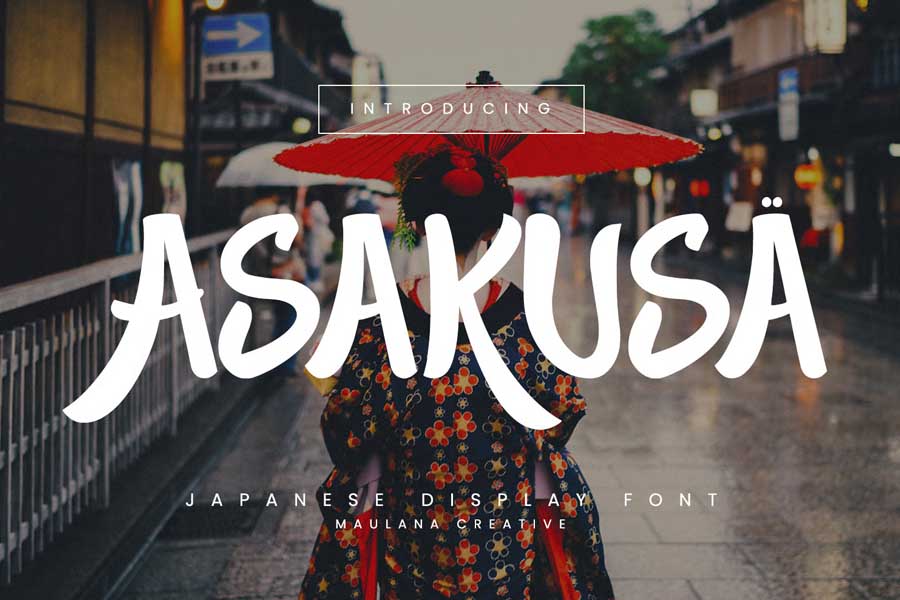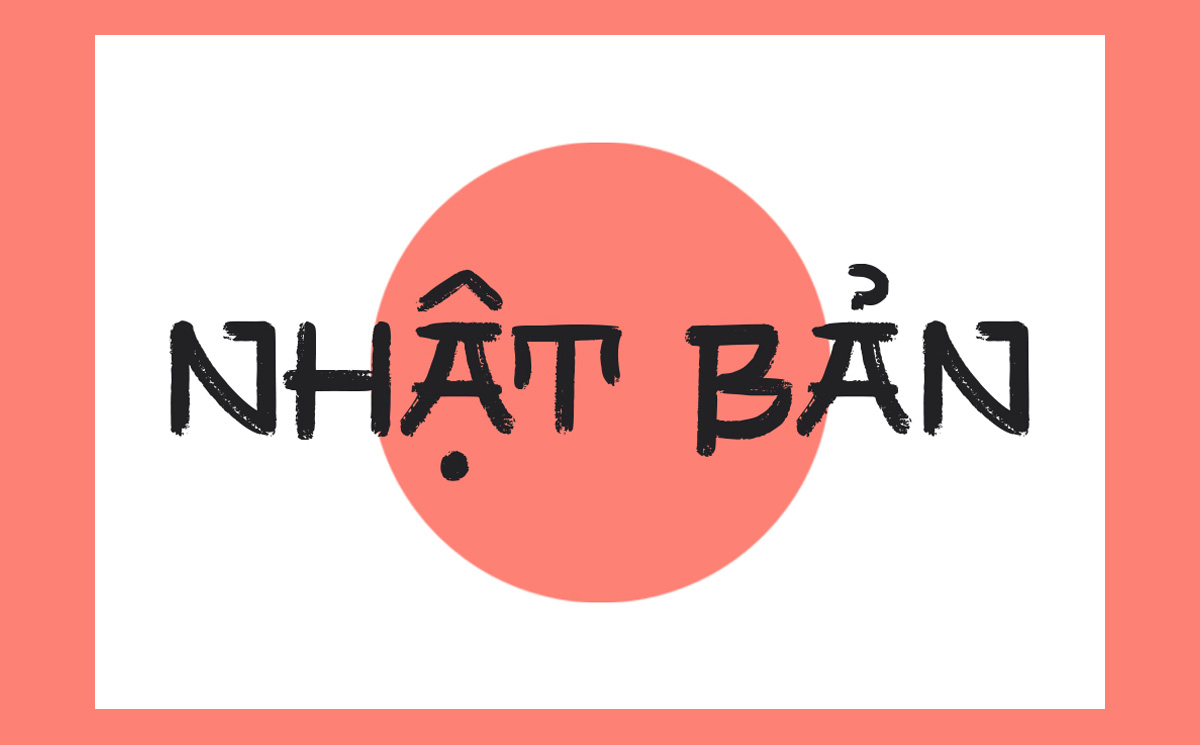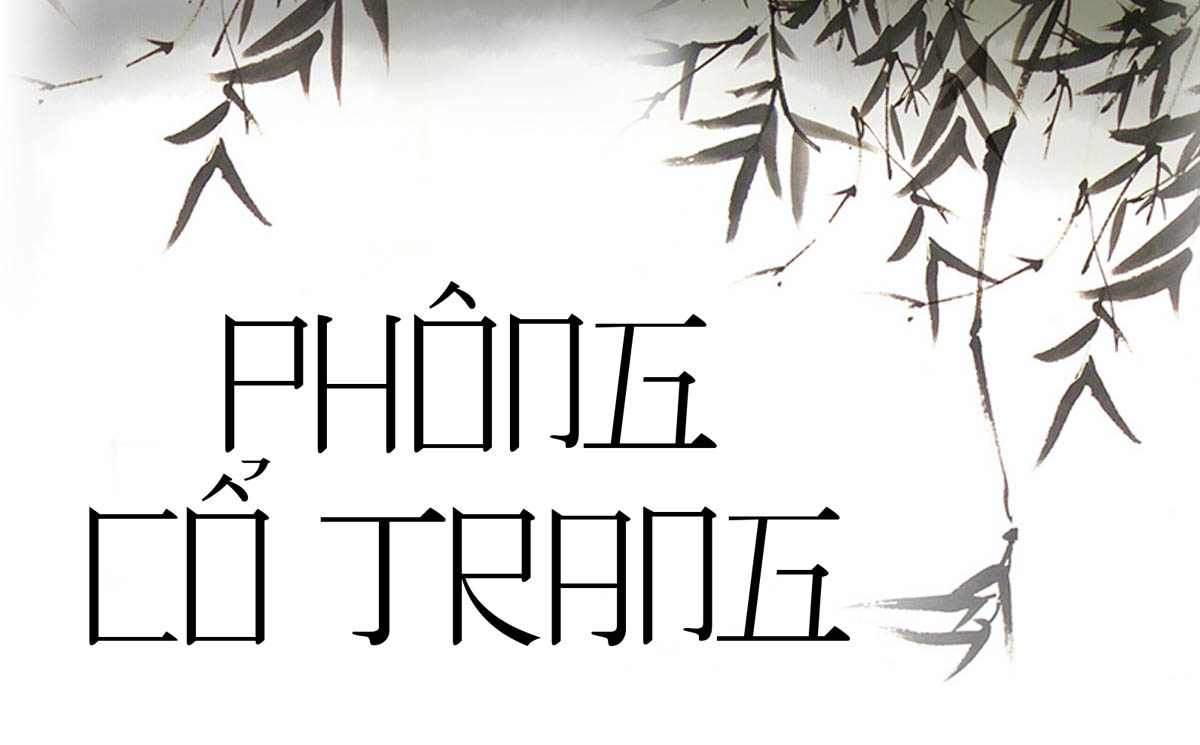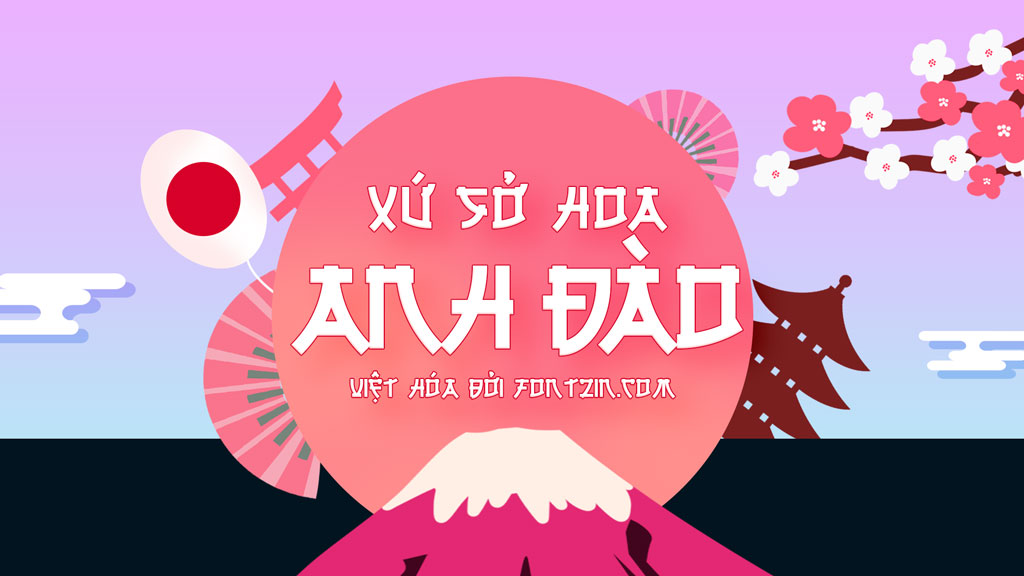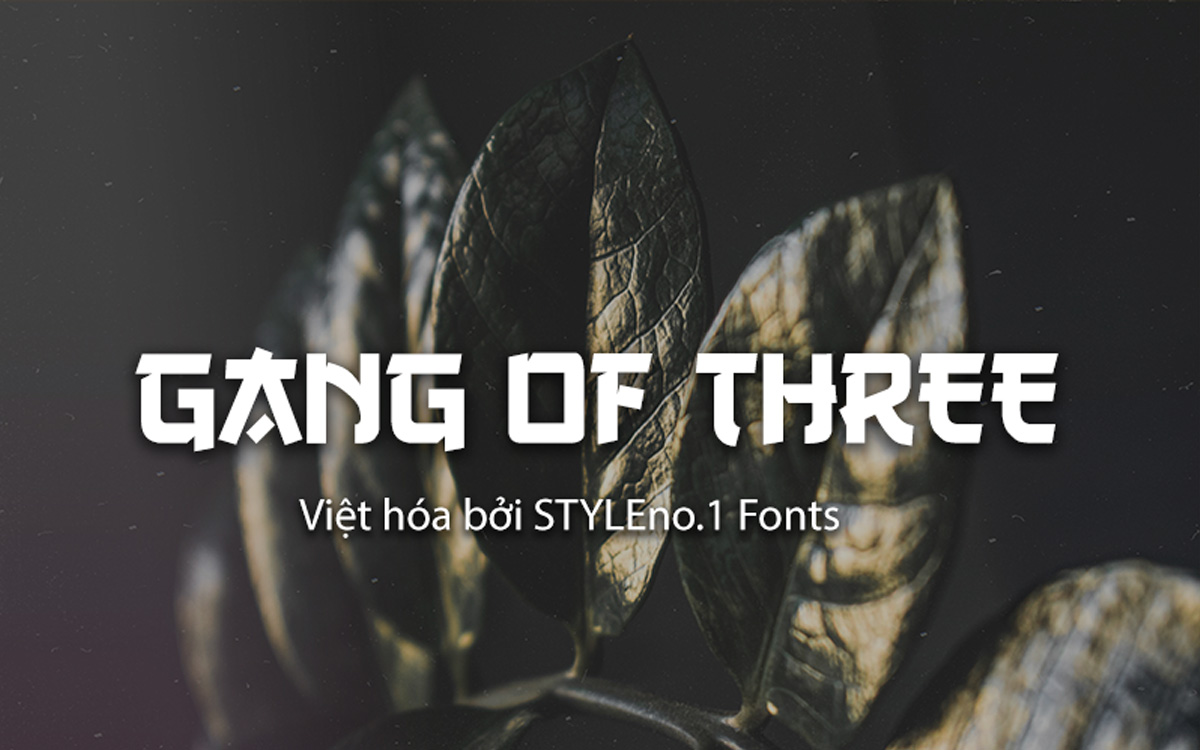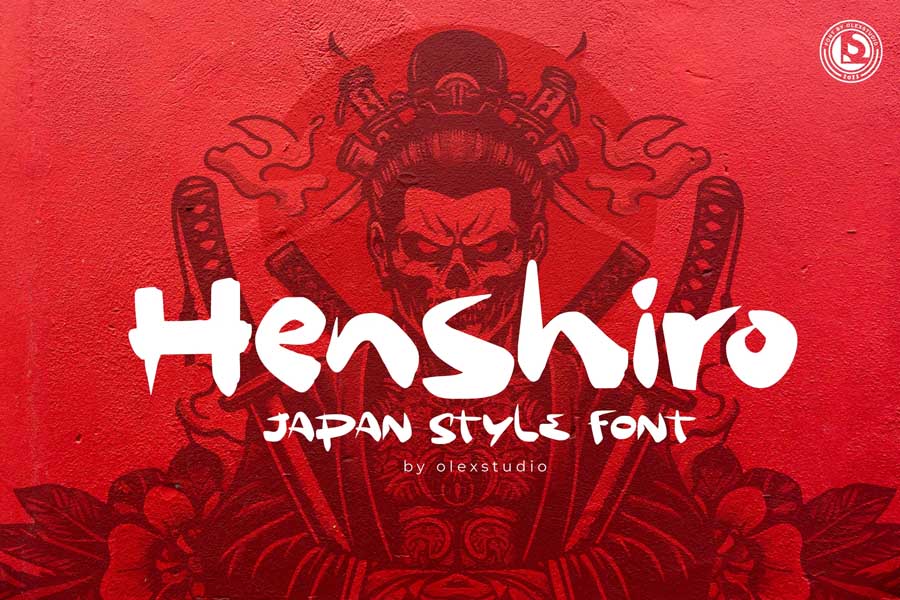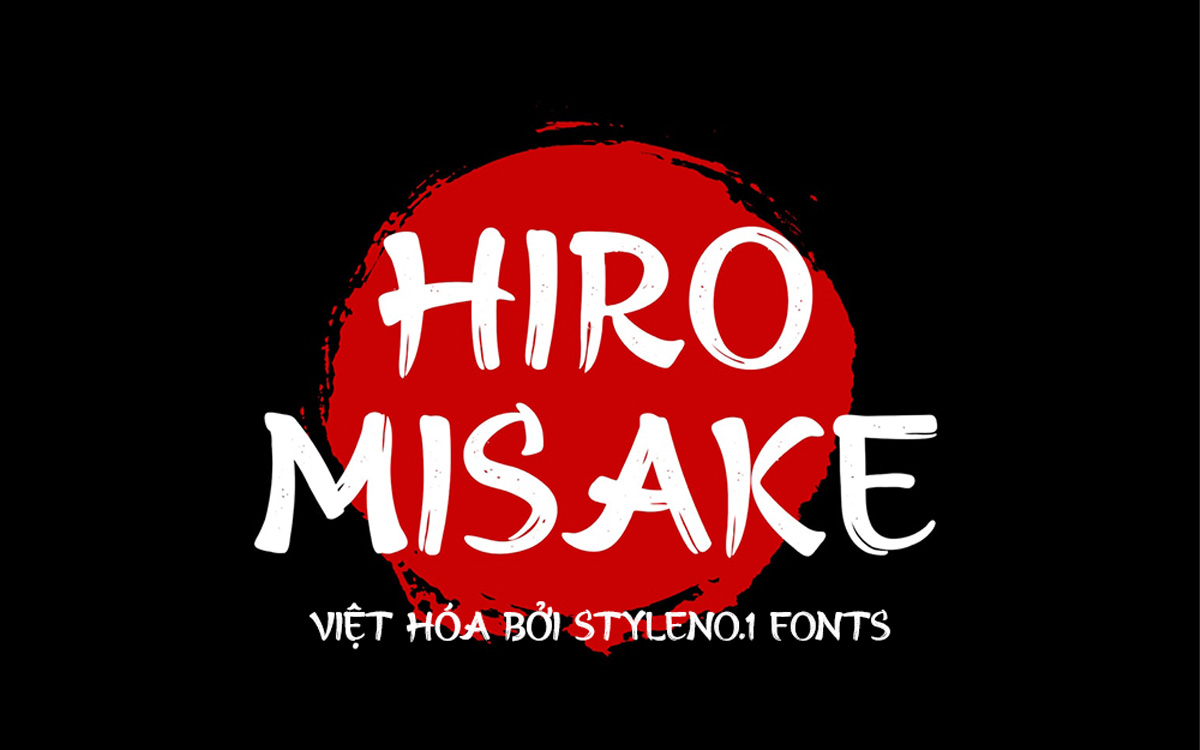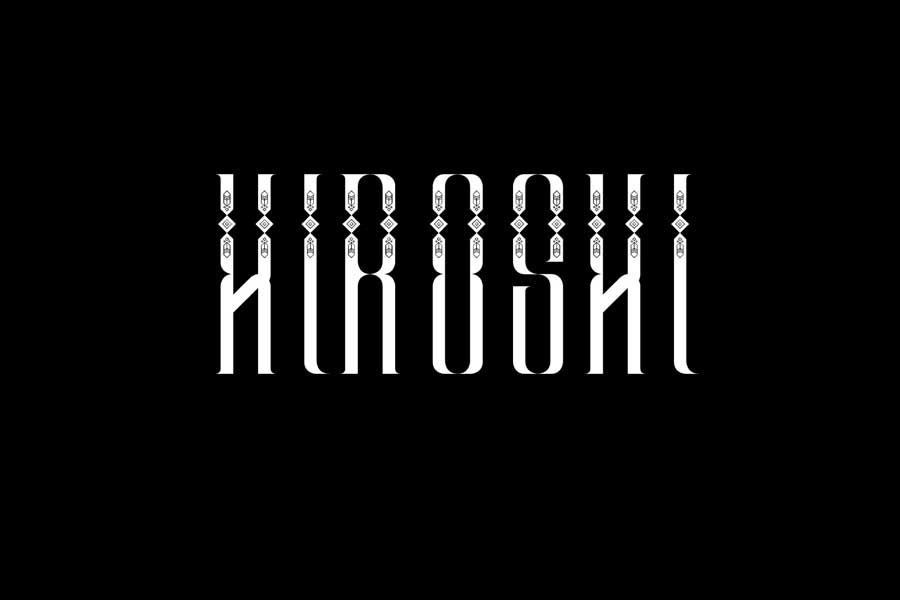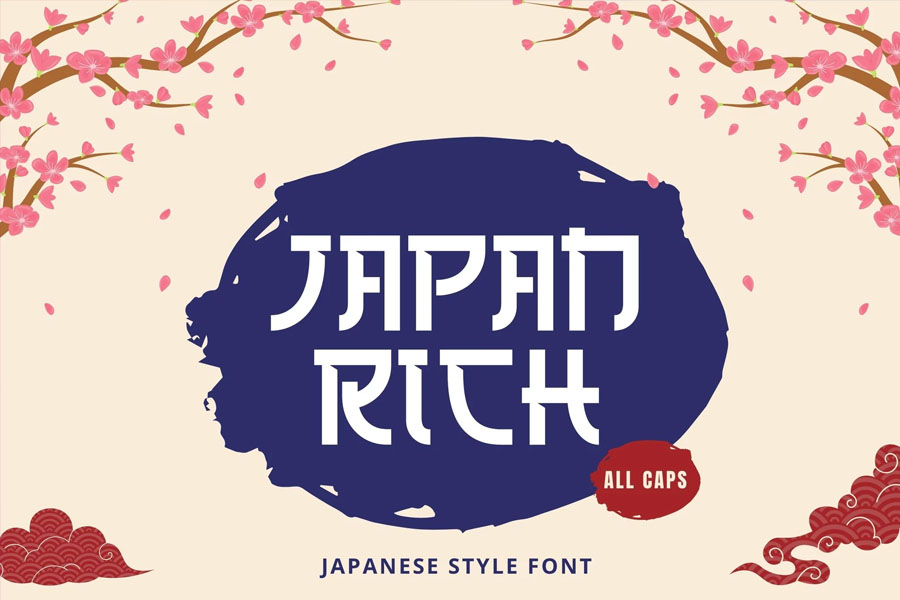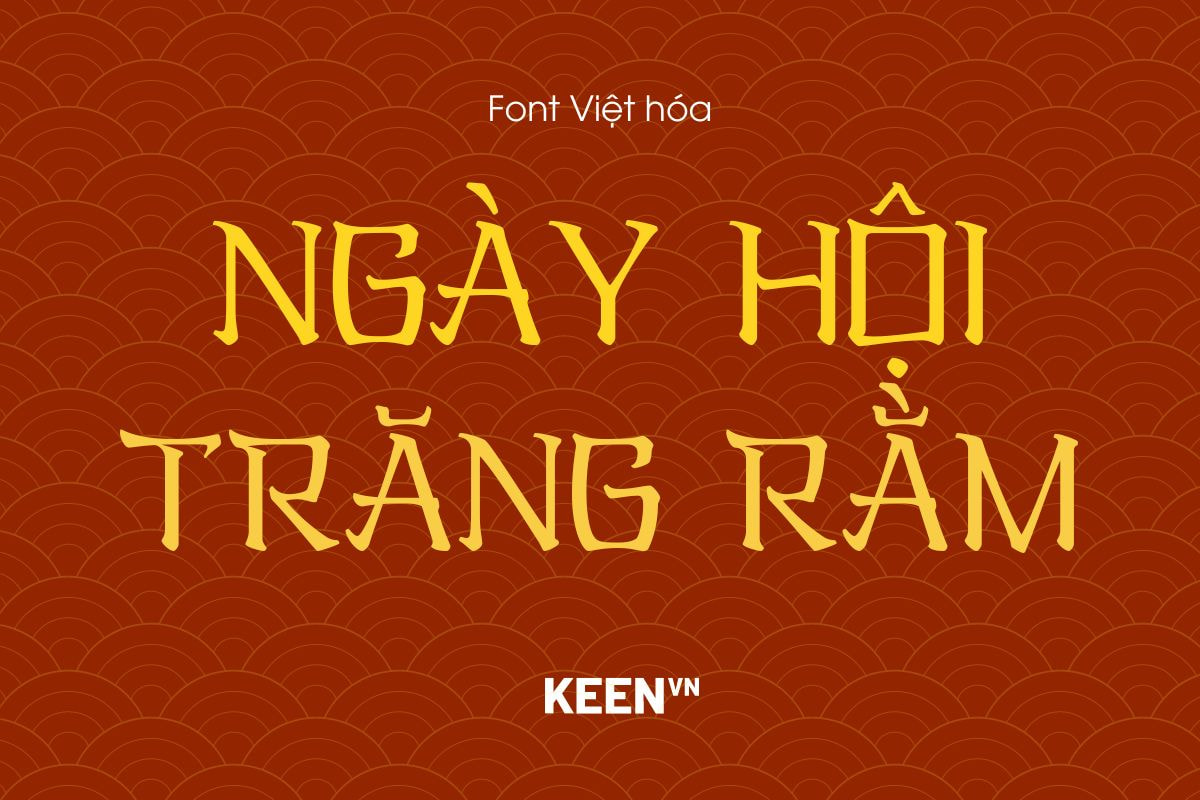
Font chữ Nhật Bản Việt hóa và nguyên bản đang trở thành lựa chọn lý tưởng cho các nhà thiết kế hiện đại. Từ những đường nét thư pháp uyển chuyển đến kiểu chữ mạnh mẽ trong anime, các font Nhật Bản không chỉ giàu tính thẩm mỹ mà còn mang đậm tinh thần văn hóa phương Đông. Bài viết này sẽ giúp bạn khám phá bộ sưu tập font chữ Nhật đẹp nhất 2025, bao gồm cả bản Việt hóa đầy đủ tiếng Việt và bản gốc chuẩn Nhật – cùng link tải cho từng font.
Font chữ Nhật Bản là gì?
Font chữ Nhật Bản là các kiểu chữ được thiết kế dựa trên bảng chữ cái tiếng Nhật (Hiragana, Katakana và Kanji) hoặc mang phong cách lấy cảm hứng từ văn hóa, thư pháp và thị giác Nhật Bản. Những font này thường có nét đặc trưng như: đường nét mềm mại, hình học sắc sảo, hoặc hiệu ứng vẽ tay đậm chất anime. Trong thiết kế hiện đại, font Nhật Bản còn bao gồm cả các kiểu Latin được stylize theo phong cách Nhật.
Font chữ Nhật có thể được chia thành hai loại chính: font gốc chưa Việt hóa và font đã Việt hóa hỗ trợ đầy đủ tiếng Việt – phù hợp với nhu cầu thiết kế của người Việt.
TOP Font chữ Nhật Bản đã được Việt hóa
Font chữ Nhật Bản đã được Việt hóa là gì?
Font chữ Nhật Bản đã Việt hóa là những kiểu chữ gốc Nhật đã được chỉnh sửa để hỗ trợ đầy đủ bảng chữ cái tiếng Việt, bao gồm các ký tự có dấu như ă, â, ê, ô, đ, sắc, huyền, hỏi, ngã, nặng. Quá trình Việt hóa không chỉ đảm bảo font hiển thị chính xác khi gõ tiếng Việt, mà còn giữ nguyên phong cách thẩm mỹ và tinh thần thiết kế gốc. Nhờ đó, người dùng có thể dễ dàng áp dụng font vào các dự án thiết kế bằng tiếng Việt mà không gặp lỗi mất ký tự hay sai lệch tỷ lệ dấu.
Danh sách các font chữ Nhật Bản đã được Việt hóa đẹp nhất 2025
Font chữ JuZho Kaizen – Brush Nhật Bản mạnh mẽ Việt hóa
JuZho Kaizen mang phong cách brush Nhật Bản hiện đại với những nét vẽ phóng khoáng và đầy năng lượng. Các đường cọ gãy gọn, không đều một cách có chủ đích, tạo cảm giác như được viết tay bằng mực thật. Tổng thể font mang đậm tinh thần đường phố, rất phù hợp cho tiêu đề anime, poster hành động hoặc thiết kế sáng tạo mang cảm hứng nghệ thuật tự do.
Font chữ SVN Romaji Mincho – Phông Nhật cổ điển thanh thoát
SVN Romaji Mincho mang dáng dấp thư pháp triện kết hợp nét viết Á Đông cách điệu. Các chữ cái được thiết kế vuông vức, thanh mảnh với phần đầu và chân có chi tiết nhọn đặc trưng, tạo nên vẻ trang trọng và cổ kính. Sự cân đối giữa hình khối và khoảng cách giúp font giữ được tính truyền thống mà vẫn rõ ràng khi trình bày văn bản. Thích hợp cho tiêu đề phim cổ trang, sách lịch sử hoặc các ấn phẩm văn hóa nghi lễ.
Font chữ Fz Tokugawa – Font Nhật mạnh mẽ, góc cạnh Việt hóa
Fz Tokugawa nổi bật với kiểu chữ đậm nét và thiết kế sắc sảo, toát lên tinh thần võ sĩ đạo đặc trưng của Nhật Bản. Các ký tự được tạo hình chắc chắn, phần đầu nét vuốt nhọn tạo cảm giác dứt khoát và đầy uy lực. Font duy trì sự đồng đều trong bố cục, mạnh mẽ nhưng không hề thô cứng. Rất thích hợp cho tiêu đề game, poster hành động hoặc các thiết kế mang hơi hướng Nhật cổ pha hiện đại.
- Việt hóa bởi: FontZin
Font chữ SVN Sigokae – Font tiếng Nhật đẹp, uốn lượn tinh tế
SVN Sigokae nổi bật nhờ các đường nét bo tròn mềm mại kết hợp chi tiết kéo đuôi đầy nghệ thuật, mang lại cảm giác tinh tế và phóng khoáng. Bộ chữ được thiết kế với tỷ lệ hài hòa giữa thân chữ và khoảng cách giữa các ký tự, tạo nên nhịp điệu thị giác êm dịu và dễ chịu. Sự kết hợp giữa hiện đại và cảm hứng truyền thống Nhật Bản giúp font phù hợp trong các thiết kế cao cấp như bìa sách, poster văn hóa, hay thương hiệu mang tính nghệ thuật.
- Tác giả gốc: GlyphStyle
- Việt hóa bởi: STYLEno.1 Fonts
Font Oriental Kaishu – Font thư pháp Nhật truyền thống Việt hóa
Oriental Kaishu mang đậm tinh thần thư pháp Á Đông với dáng chữ được thiết kế chỉnh chu, kết hợp các nét móc nhẹ ở phần chân tạo cảm giác mềm mại nhưng vẫn giữ được sự trang trọng. Các ký tự có độ đều đặn cao, giúp tổng thể trở nên cân đối và dễ nhìn. Dấu tiếng Việt được xử lý tinh tế, đảm bảo không làm ảnh hưởng đến nhịp điệu thị giác của font. Rất phù hợp cho thiết kế tiêu đề lễ hội, ấn phẩm văn hóa hoặc bảng hiệu mang phong cách truyền thống.
- Tác giả gốc: Alexander Bobrov
- Việt hóa bởi: STYLEno.1 Fonts
Font Money Game – Font Nhật phong cách anime hiện đại
Money Game sở hữu kiểu chữ hình học chắc chắn với các nét thẳng vuông góc và khối chữ lớn, tạo cảm giác mạnh mẽ và đầy áp lực. Các ký tự mang phong cách digital đậm chất Hàn – Nhật, dễ liên tưởng đến trò chơi sinh tồn hay các thiết kế game kịch tính. Phong cách độc đáo này giúp tiêu đề nổi bật, đặc biệt hiệu quả khi sử dụng trong poster phim, dự án giải trí hoặc các ấn phẩm mang tính kịch bản viễn tưởng.
- Với font chưa Việt hóa, chỉ nên dùng cho tiêu đề không dấu.
Font chữ Nhật Bản không chỉ độc đáo về hình thức mà còn mang đậm tinh thần văn hóa Á Đông. Dù bạn thiết kế poster, logo, tiêu đề hay bao bì – bộ font trong bài viết này đều có thể giúp bạn tạo dấu ấn riêng biệt.